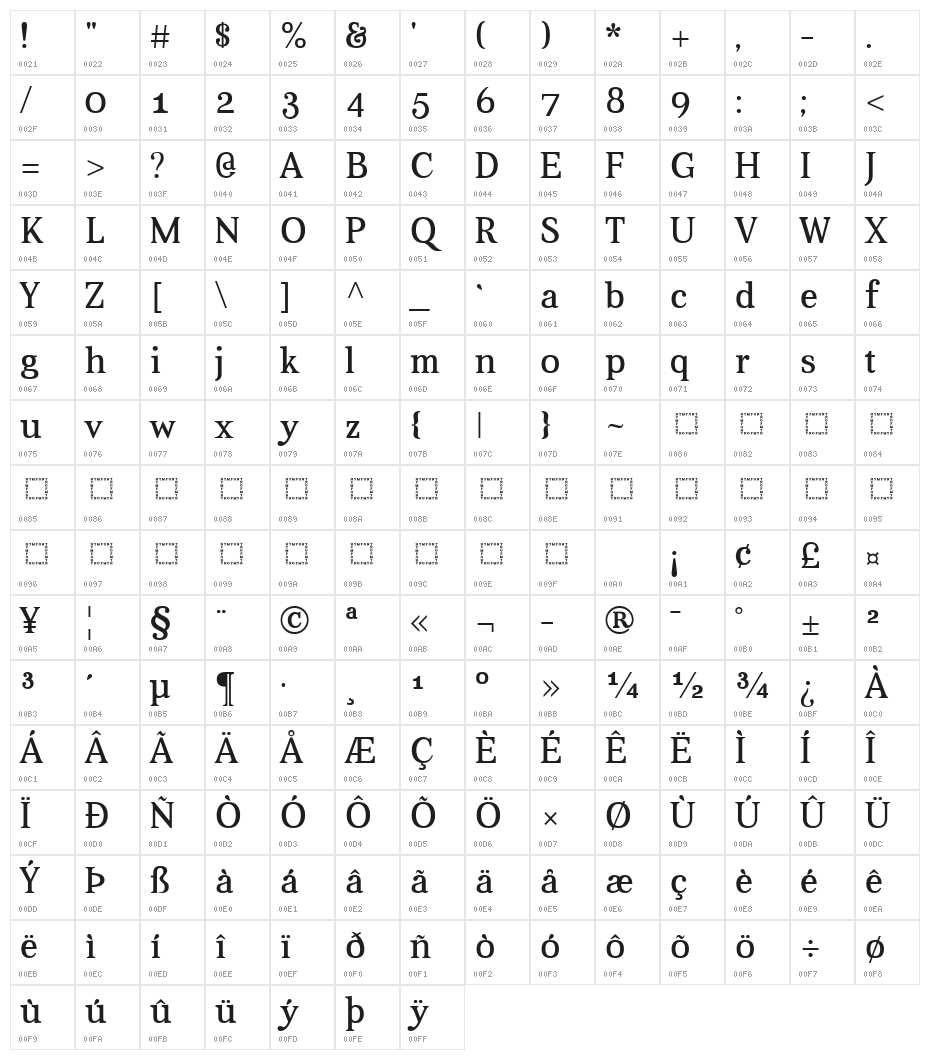
Aver Font
✎ Serif
| Progetti proposti | Ideal for editorial design, book covers, formal invitations, and branding projects that require a touch of sophistication. |